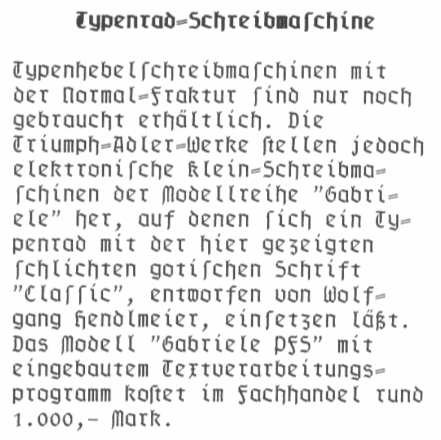
Was gibt es an gebrochenen Schreibmaschinenfonts …
… außer der F25 Blackletter Typewriter?
Ich kann mich erinnern, mal einen Font gesehen zu haben, welcher sich von der F25 in einigem unterscheidet; zB war dort nach meiner Erinnerung die Unterlänge des kleinen «h» nach innen gebogen, nicht wie bei F25 nach außen.
Kennt jemand diesen, oder weitere?
Als Reproduktion von Schreibmaschinenschriften ist mir nur die F25 Blackletter bekannt. Wenn Dir eine monospaced reichen würde, kann die Pragmata Pro auch noch Fraktur.
Hast du evtl. ein Bild wie dieses im Gedächtnis? So mit Farbbandspuren? Da ist mir leider bisher auch noch kein Font untergekommen ...
Als Reproduktion von Schreibmaschinenschriften ist mir nur die F25 Blackletter bekannt. Wenn Dir eine monospaced reichen würde, kann die Pragmata Pro auch noch Fraktur.
Sieht auch gut aus!
Noch kein fertiges Produkt aber evtl passend, die Horst von Falk Schwabe : http://26plus-zeichen.de/fonts/horst/
Auch ein tolles Projekt, wann wird das fertig sein?
Hast du evtl. ein Bild wie dieses im Gedächtnis? So mit Farbbandspuren? Da ist mir leider bisher auch noch kein Font untergekommen ...
Ich fürchte, der Font, an den ich mich zu erinnern glaube, war zwar auf dem Bildschirm, allerdings: vielleicht war es ein Spielfilm aus dem Genre «Steam Punk», oder dergleichen, wo dieser Font vorkam.
[Gab es nicht eine (finnische?) Science-Fiction-Komödie mit «Nazis auf dem Mond» vor ein paar Jahren? Dieser oder etwas in der Art könnte es gewesen sein, denke ich inzwischen.]
Vielleicht erinnere ich mich doch an etwas Reales, und es war nicht aus einem Spielfilm, denn:
In 1992, he created Classic, a blackletter typewriter font.
Die Rede ist von Herrn Hendlmeier, siehe http://luc.devroye.org/fonts-41719.html
Ah, Abbildung setze ich noch eine Kopie hinein, falls obiges Original nicht erreichbar ist:
(Wobei es sich nach dem dortigen Text jedoch um physische/mechanische Typen und nicht eine Datei handelt, oder?)